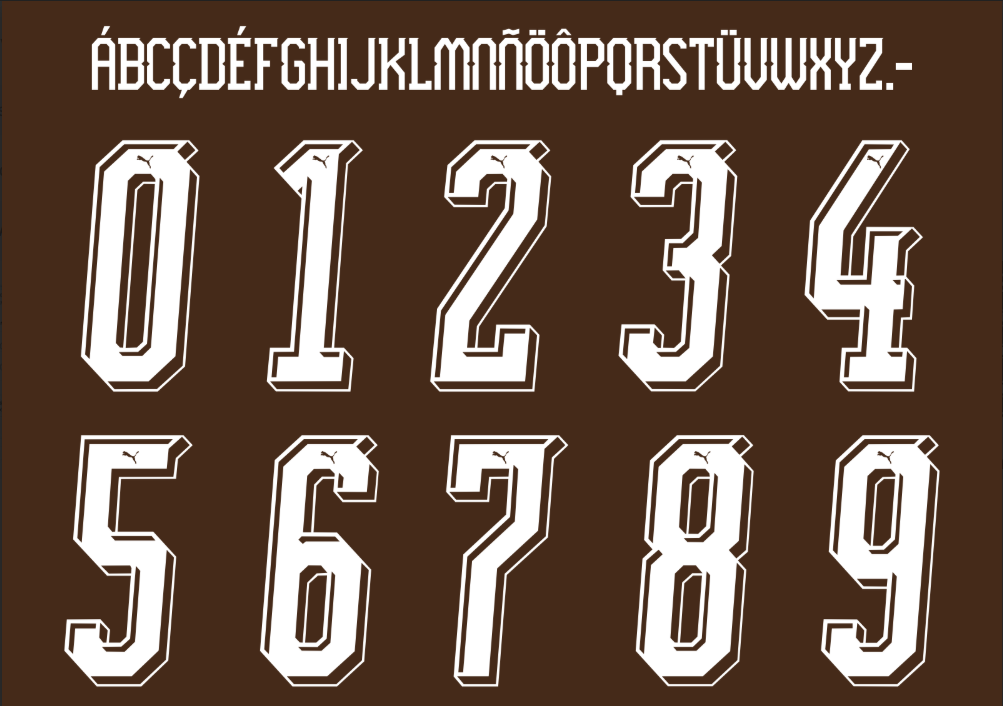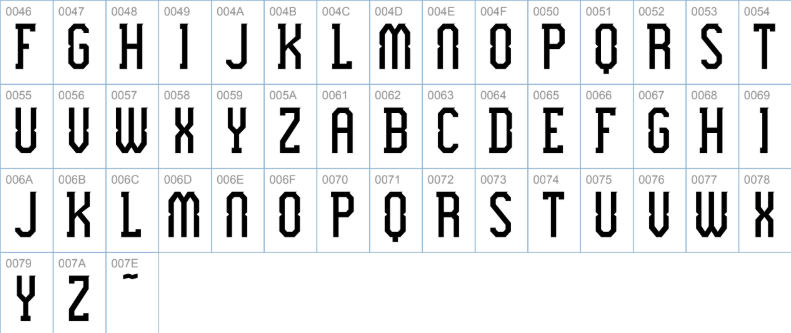
O futebol argentino respira tradição, e o Club Atlético Platense é uma prova viva disso. Para a temporada 2026, a parceria com a dinamarquesa Puma continua rendendo frutos, entregando uniformes que honram a identidade visual única do “Calamar” com o clássico marrom e branco.
Estilo Visual da Tipografia
A Puma costuma trazer personalidade para suas fontes, e no Platense 2026 não foi diferente. A tipografia aposta em um design geométrico e condensado, ideal para nomes longos nas costas das camisas.
Os números possuem traços retos e uma espessura média, garantindo uma leitura clara sem poluir o visual clássico da camisa, que geralmente possui a faixa horizontal marrom. É uma fonte que mistura a estética europeia da marca com a garra do futebol argentino, resultando em um visual sóbrio e moderno.